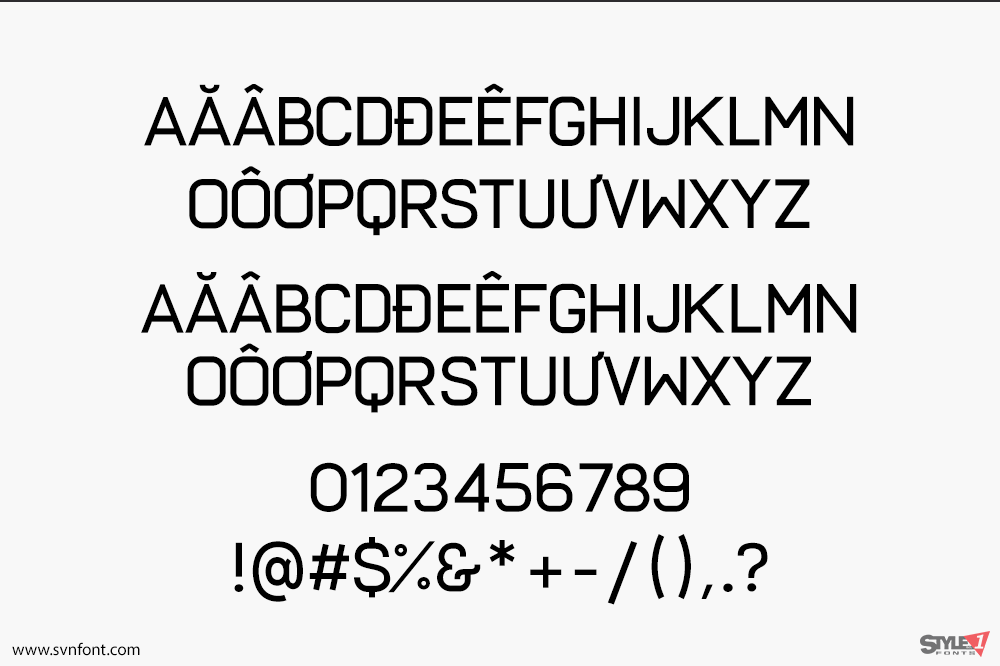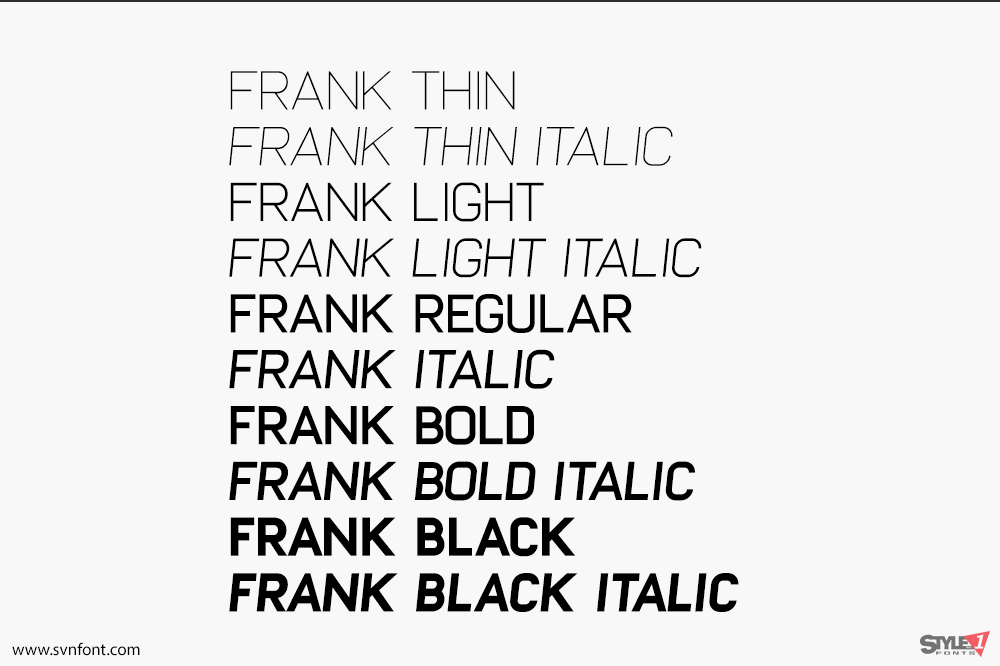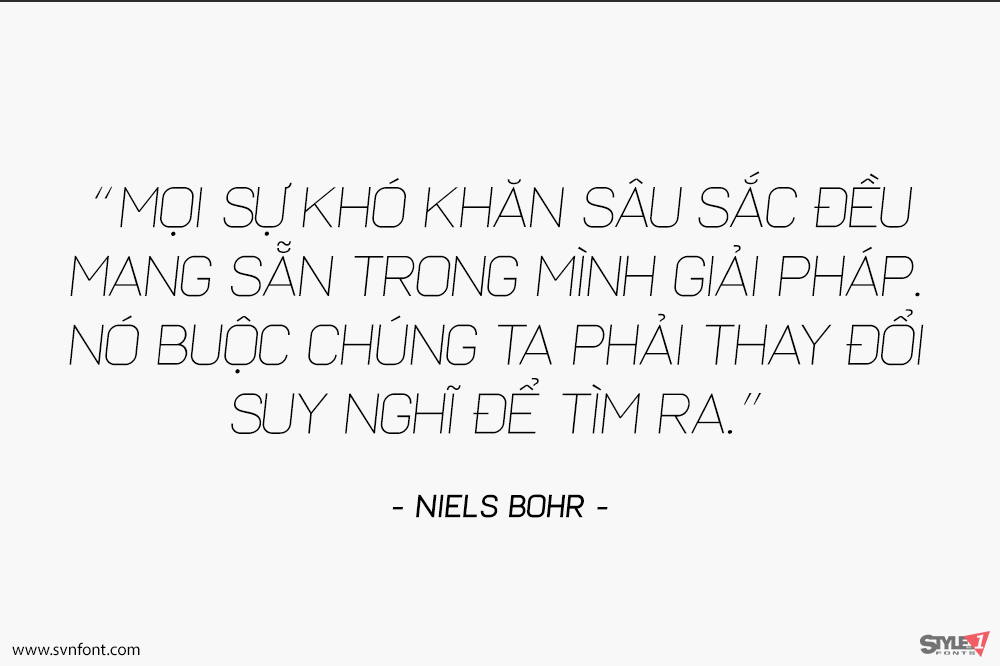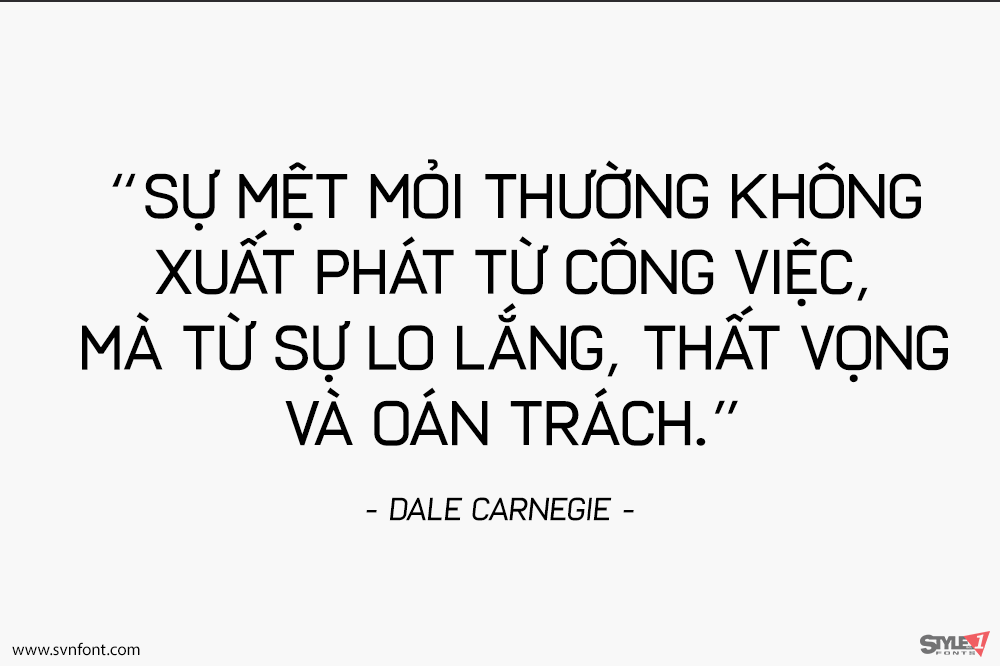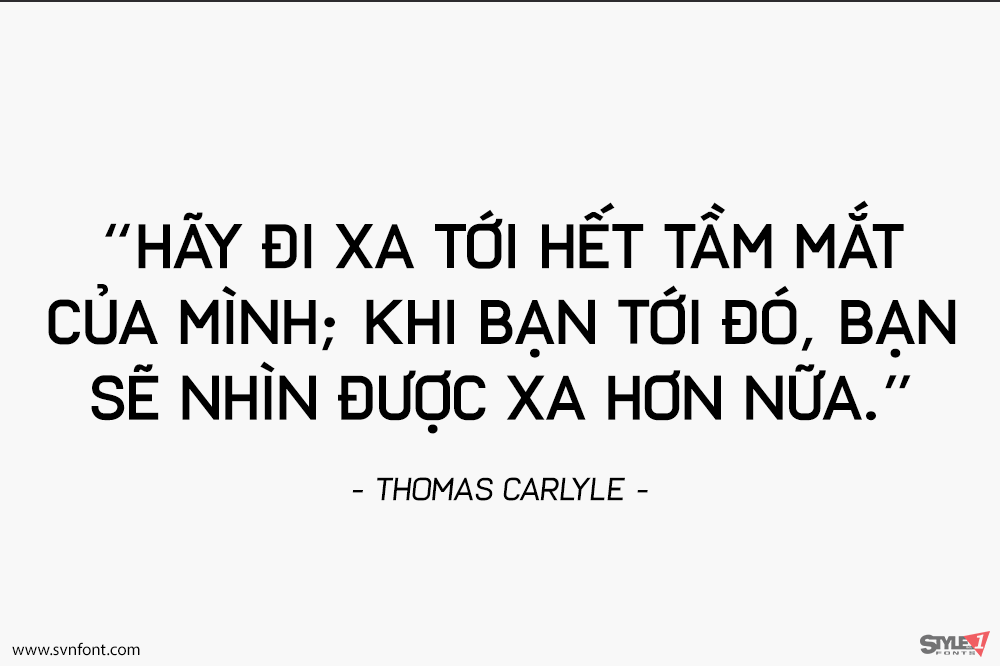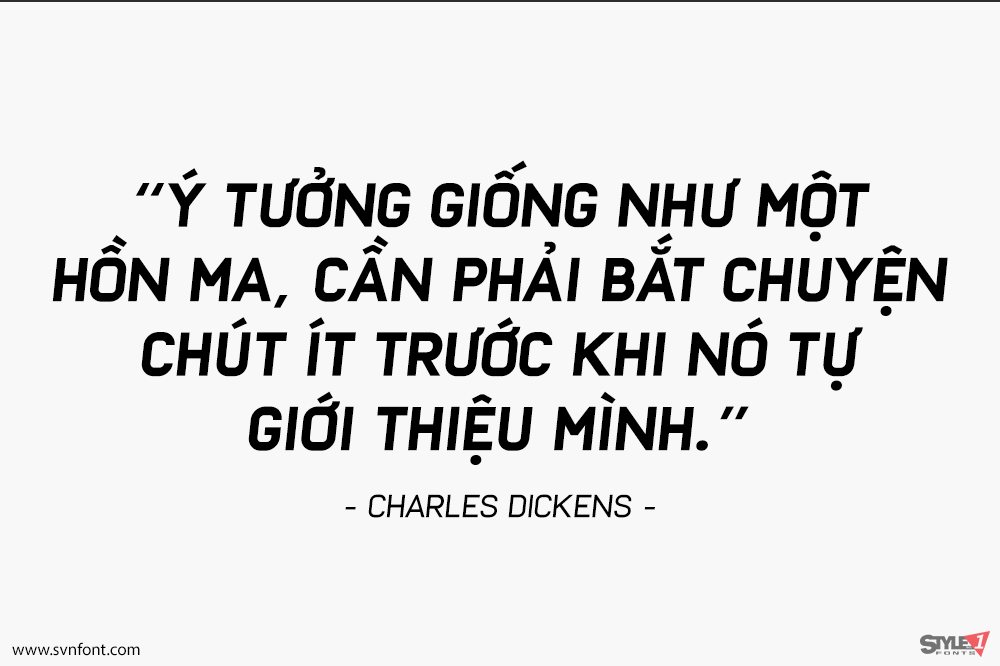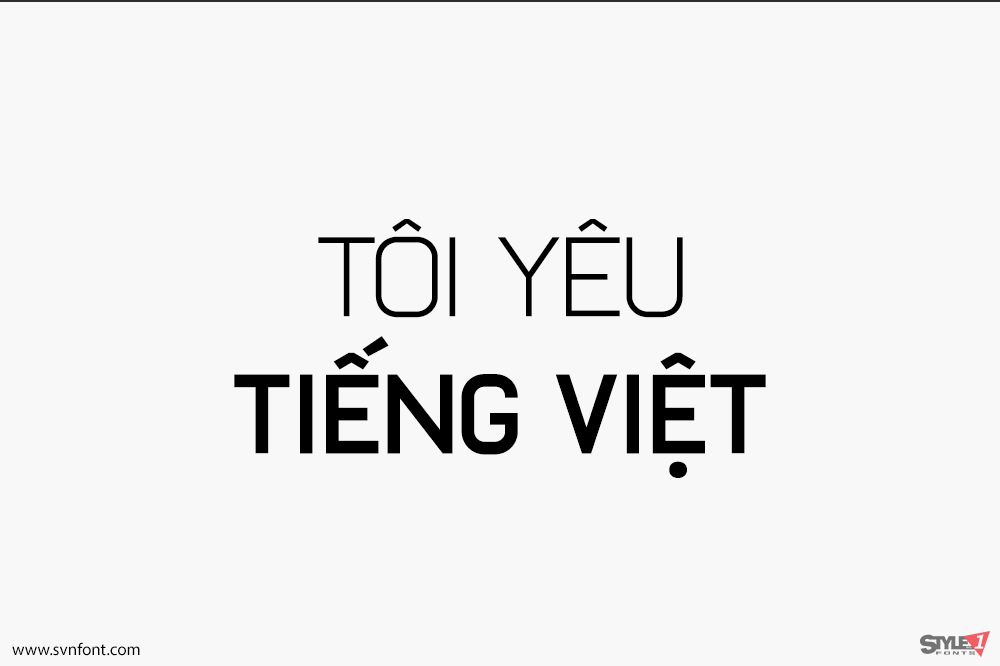
Tự hào giới thiệu phông chữ Frank được lấy cảm hứng từ các phông cổ điển như DIN, Eurostile và một chút của Futura. Hoàn hảo cho các bản in, áo phông, poster và những thứ tương tự.
Nhà thiết kế: Great Scott!
Nhà phát hành: Great Scott!